فراكتورا
فراكتور ( الألمانية: [ fʁakˈtuːɐ̯ ]ⓘ ) هوخط كتابيللأبجديةاللاتينية، وهو أحدالقوطيةالمشتقة منه. صُمم بحيث تكون بدايات ونهايات الخطوط المكونة لكل حرف واضحة، وغالبًا ما يتم إبرازها؛ وبهذه الطريقة، غالبًا ما يُقارن بمنحنياتAntiqua(العادية) حيث صُممت الحروف لتتدفق وتتصل الخطوط ببعضها البعض بشكل مستمر. كلمة "Fraktur" مشتقة من الكلمةاللاتينية frāctūra ("كسر")، المبنية من frāctus ، وهو اسم المفعول من frangere ("يكسر")، وهو أيضًا جذر الكلمة الإنجليزية "fracture" (كسر). في السياقات غير الاحترافية، يُساء استخدام مصطلح "Fraktur" أحيانًا للإشارة إلىجميعالخطوط القوطية-في حين أن خطوط Fraktur تندرج تحت هذه الفئة، إلا أن ليس كل الخطوط القوطية تُظهر خصائص Fraktur الموصوفة أعلاه. [ أ ]
يُوصف خط فراكتور غالبًا بأنه "الخط الألماني"، إذ ظل شائعًا في ألمانيا ومعظم أنحاء أوروبا الشرقية لفترة أطول بكثير من غيره. وابتداءً من القرن التاسع عشر، كان استخدام فراكتور مقابل أنتيكوا (الذي يُعتبر حديثًا) موضع جدل في ألمانيا. واستمر هذا الجدل حتى عام ١٩٤١، حين حظرت الحكومة النازية خطوط فراكتور؛ ولا يزال استخدامها محدودًا حتى اليوم.
صفات
إلى جانب الأحرف الستة والعشرين للأبجدية اللاتينية الأساسية ISO ، يتضمن خط فراكتورا عادةً حرف إسزيت ⟨ß⟩ في شكل ⟨ſʒ⟩ ، وحروف العلة مع علامات التشكيل ، وحرف السين الطويل ⟨ſ⟩ . كما تتضمن بعض خطوط فراكتورا شكلاً مختلفاً لحرف الراء يُعرف باسم r rotunda ، ويحتوي العديد منها على مجموعة متنوعة من الوصلات المتبقية من الكتابة اليدوية المتصلة، والتي لها قواعد استخدامها. لا تُميّز معظم خطوط فراكتورا القديمة بين الحرفين الكبيرين ⟨I⟩ و⟨ J⟩ ( حيث يكون الشكل المشترك أقرب إلى ⟨J⟩ ) ، على الرغم من التمييز بين الحرفين الصغيرين ⟨i⟩ و⟨ j⟩ .
يتمثل أحد الفروق بين خط فراكتورا وخطوط الكتابة القوطية الأخرى في أن الجزء الأيسر من حرف ⟨o⟩ الصغير يكون مكسورًا، بينما يكون الجزء الأيمن سليمًا. في النصوص الدنماركية المكتوبة بخط فراكتورا، كان الحرف ⟨ø⟩ مفضلًا على الحرف الألماني والسويدي ⟨ö⟩ منذ القرن السادس عشر. [ ج ]
في النسخة اللاتفية من خط فراكتورا، المستخدمة بشكل رئيسي حتى عشرينيات القرن العشرين، توجد أحرف إضافية تستخدم للدلالة على الأحرف اللاتفية ذات العلامات التشكيلية . [ 1 ] [ 2 ] تُستخدم الأحرف المشطوبة ⟨Ꞡꞡ⟩ ، ⟨Ꞣꞣ⟩ ، ⟨Łł⟩ ، ⟨Ꞥꞥ⟩ ، ⟨Ꞧꞧ⟩ للأصوات الساكنة الحنكية ( ⟨Ģģ⟩ ، ⟨Ķķ⟩ ، ⟨Ļļ⟩ ، ⟨Ņņ⟩ ، ⟨Ŗŗ⟩ ) ، بينما تُستخدم الأشكال المشطوبة من ⟨s⟩ و⟨ ſ⟩ لتمييز الأصوات الاحتكاكية المجهورة وغير المجهورة ( ⟨Sſ ) . يُستخدم الرمز ⟩ للحرف [z] المجهور، والرمز ⟨Ꞩẜ⟩ للحرف [s] المهموس، والرمز ⟨ſch⟩ للحرف [ ž ] / ⟨ẜch⟩ للحرف [ š ]، والرمز ⟨dſch⟩ للحرف [ dž ] / ⟨tẜch⟩ للحرف [ č ] ، بينما تُستخدم علامات التشكيل ( ⟨à⟩، ⟨â⟩ ، ⟨ê⟩ ، ⟨î⟩ ، ⟨ô⟩ ، ⟨û⟩ ) مع الحروف المركبة ( ⟨ah⟩ ، ⟨eh⟩ ، إلخ ) للأصوات المتحركة الطويلة ( ⟨Āā⟩ ، ⟨ Ē ē ⟩ , ⟨ Ī ī ⟩ , ⟨ Ō ō ⟩ , ⟨ Ū ū ⟩ ). تُستخدم أيضًا الأشكال المتنوعة من ⟨ s ⟩ في قواعد الإملاء الصوربية قبل عام 1950. [ 1 ]
أصل
ظهر أول خط فراكتوري في أوائل القرن السادس عشر، عندما كلف الإمبراطور ماكسيميليان الأول ألبرخت دورر بتصميم نقش قوس النصر الخشبي ، وأمر بإنشاء خط جديد خصيصًا لهذا الغرض، صممه هيرونيموس أندريا . وقد اعتمد الناشر يوهان شونسبرغر من أوغسبورغ خطوط فراكتوري للطباعة عند إصدار سلسلة من أعمال ماكسيميليان، مثل كتاب صلاته ( Gebetbuch ، 1513) أو قصيدة ثويردانك المصورة (1517). [ 3 ]
سرعان ما تفوقت خطوط فراكتور على خطوط شواباشر وتيكستواليس السابقة من حيث الشعبية، ونُحتت مجموعة واسعة من خطوط فراكتور وأصبحت شائعة في العالم الناطق بالألمانية والمناطق الخاضعة للنفوذ الألماني (اسكندنافيا، إستونيا، لاتفيا، أوروبا الوسطى ). في القرن الثامن عشر، طوّر يوهان غوتلوب إيمانويل برايتكوف، مصمم الخطوط من لايبزيغ، خط فراكتور الألماني ثيوردانك ليُنتج خط برايتكوف فراكتور . وبينما تحوّل معظم سكان أوروبا الوسطى إلى خط أنتيكوا على مر القرون اللاحقة ، ظلّ الناطقون بالألمانية فئةً بارزةً تُقاوم استخدام خط فراكتور.
يستخدم
كان استخدام خط فراكتور شائعًا جدًا في أوائل القرن العشرين في جميع البلدان والمناطق الناطقة بالألمانية ، وكذلك في النرويج وإستونيا ولاتفيا ، وكان لا يزال يُستخدم على نطاق ضيق جدًا في السويد وفنلندا والدنمارك ، على الرغم من أن بلدانًا أخرى كانت تستخدم خط أنتيكوا . استخدمت بعض الكتب في ذلك الوقت خطوطًا مشابهة من الخط القوطي مثل شواباشر ؛ ومع ذلك، كان الخط السائد هو نورمالفراكتور، الذي كان يأتي باختلافات طفيفة.
منذ أواخر القرن الثامن عشر وحتى أواخر القرن التاسع عشر، حلت خط أنتيكوا تدريجيًا محل خط فراكتورا كرمز للعصر الكلاسيكي والنزعة العالمية الناشئة في معظم الدول الأوروبية التي كانت تستخدم فراكتورا سابقًا. وقد أثار هذا التحول جدلًا واسعًا في ألمانيا، عُرف باسم نزاع أنتيكوا-فراكتورا . وأثر هذا التحول بشكل رئيسي على الكتابات العلمية في ألمانيا، بينما استمر نشر معظم الأدبيات والصحف بخط فراكتورا .
استمر استخدام خطوط فراكتور في ألمانيا النازية ، حيث عُرضت في البداية على أنها خط ألماني أصيل؛ فقد استُخدم هذا الخط في الوثائق الرسمية النازية ورؤوس الرسائل، كما استُخدمت نسخة مرسومة يدويًا منه على غلاف كتاب هتلر " كفاحي" . [ 6 ] مع ذلك، كانت الخطوط الأكثر حداثة من نوع "جيبروشين غروتسك"، مثل "تاننبرغ"، هي الأكثر شيوعًا في ألمانيا النازية، لا سيما في النصوص المتصلة، على عكس الاستخدامات الزخرفية كالعناوين. صُممت هذه الخطوط في أوائل القرن العشرين، وتحديدًا في ثلاثينياته، كنسخ غروتسكية من الخطوط القوطية. استخدم النازيون هذه الخطوط بكثرة، رغم أن هذا التحول ظل مثيرًا للجدل؛ بل إن الصحافة وُجهت إليها انتقادات في بعض الأحيان لاستخدامها المتكرر "للأحرف اللاتينية" تحت "التأثير اليهودي"، وحُثّ المهاجرون الألمان على استخدام "الخط الألماني" فقط. [ 7 ] [ 8 ] في 3 يناير 1941، أنهى الحزب النازي هذا الجدل بالتحول إلى استخدام خطوط دولية مثل خط أنتيكوا . أصدر مارتن بورمان تعميمًا ( مرسوم الخط العادي ) إلى جميع المكاتب العامة يُعلن فيه أن خط فراكتورا (وما يترتب عليه من خط سوتيرلين ) هو خط يهودي، وحظر استخدامه. [ 9 ] تكهن المؤرخ الألماني ألبرت كابر بأن النظام اعتبر خط فراكتورا عائقًا أمام التواصل في الأراضي المحتلة خلال الحرب العالمية الثانية . [ 10 ]
بعد سقوط ألمانيا النازية عام 1945، تم رفع الحظر عن خط فراكتورا، ولكنه لا يزال يُستخدم بشكل محدود حتى يومنا هذا. [ 11 ]
نماذج الخطوط
في الأشكال أدناه، تظهر الجملة الألمانية التي تلي أسماء الخطوط (Walbaum-Fraktur في الشكل 1 وHumboldtfraktur في الشكل 2) وهي: Victor jagt zwölf Boxkämpfer quer über den Sylter Deich . وتعني "فيكتور يطارد اثني عشر ملاكمًا عبر سد سيلت "، وتحتوي على جميع حروف الأبجدية الألمانية الستة والعشرين بالإضافة إلى الأحرف المُشكّلة بعلامة التشكيل المستخدمة في اللغة الألمانية، مما يجعلها مثالًا على الجملة الجامعة .
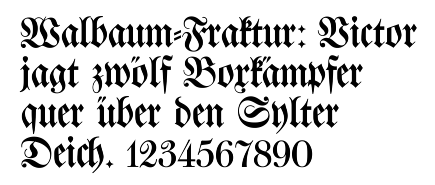
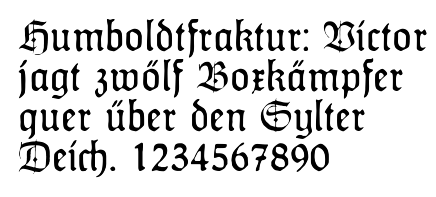
يونيكود
لا يُشفّر نظام يونيكود خط فراكتورا كخط منفصل، بل يُعتبر فراكتورا شكلاً من أشكال الأبجدية اللاتينية. [ 12 ] [ هـ ] وبالتالي، فإنّ الوصلات الإضافية المطلوبة لخطوط فراكتورا لن تُشفّر في يونيكود، إذ يُعدّ دعم هذه الوصلات مسألة هندسية خاصة بالخطوط، متروكة لمطوري الخطوط. [ 13 ]